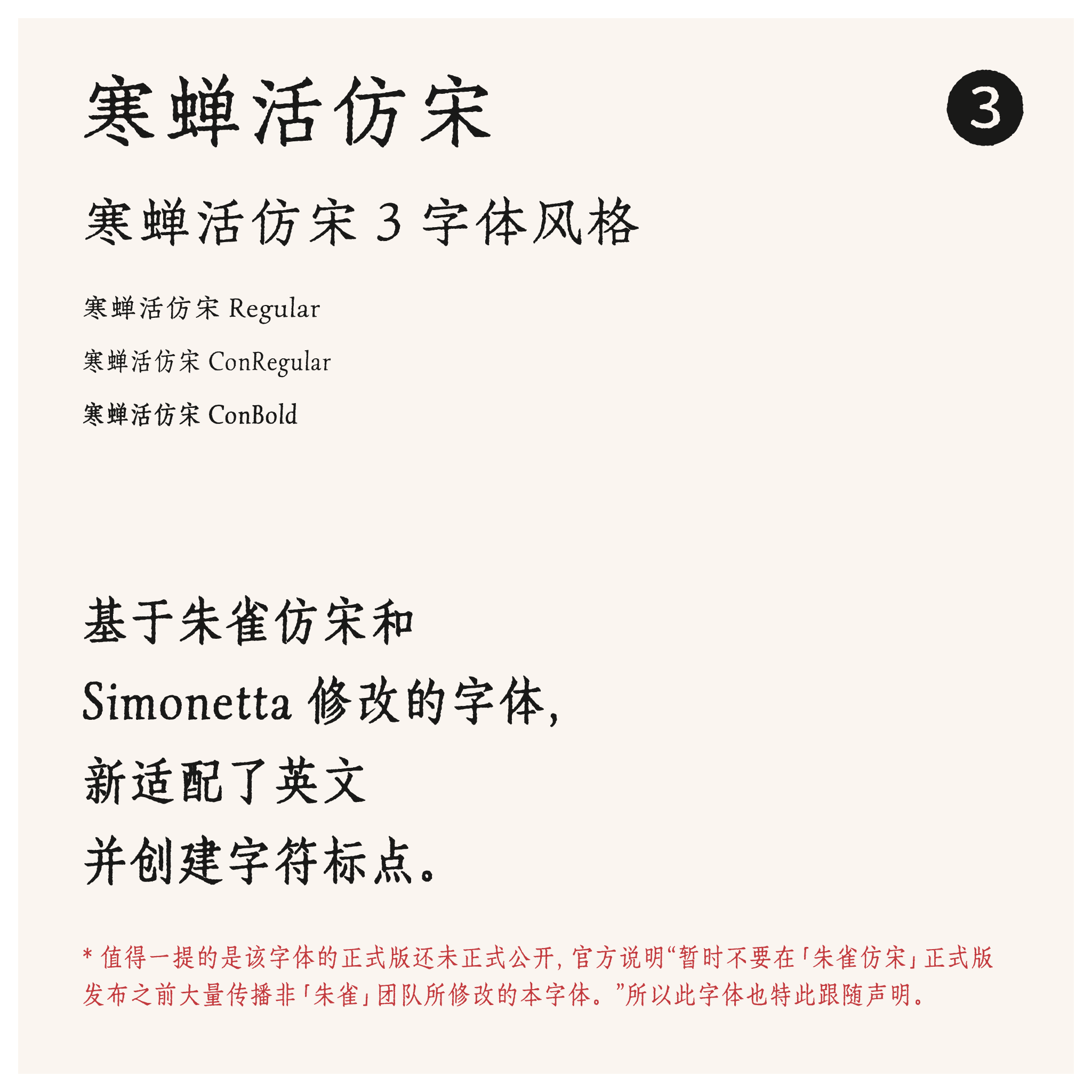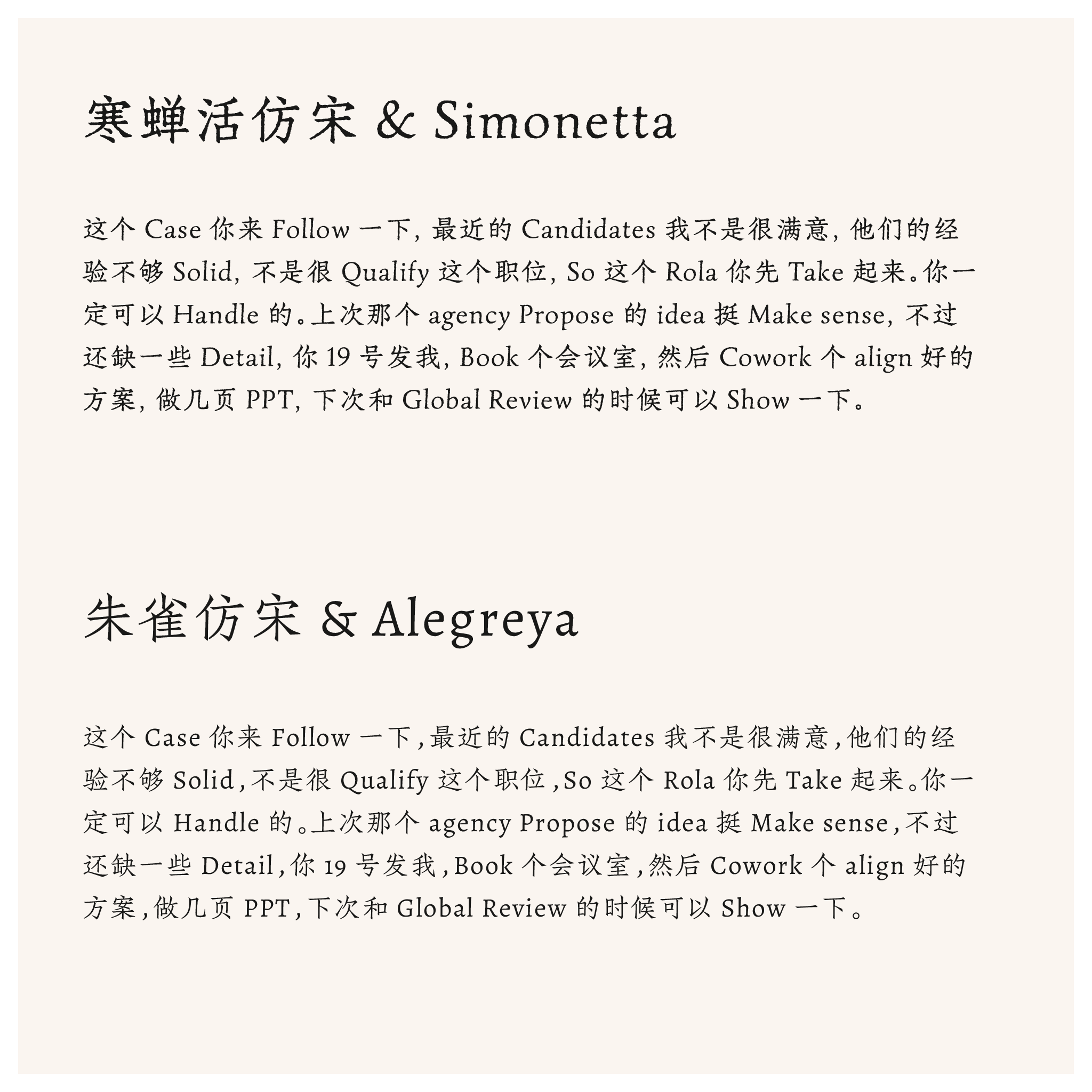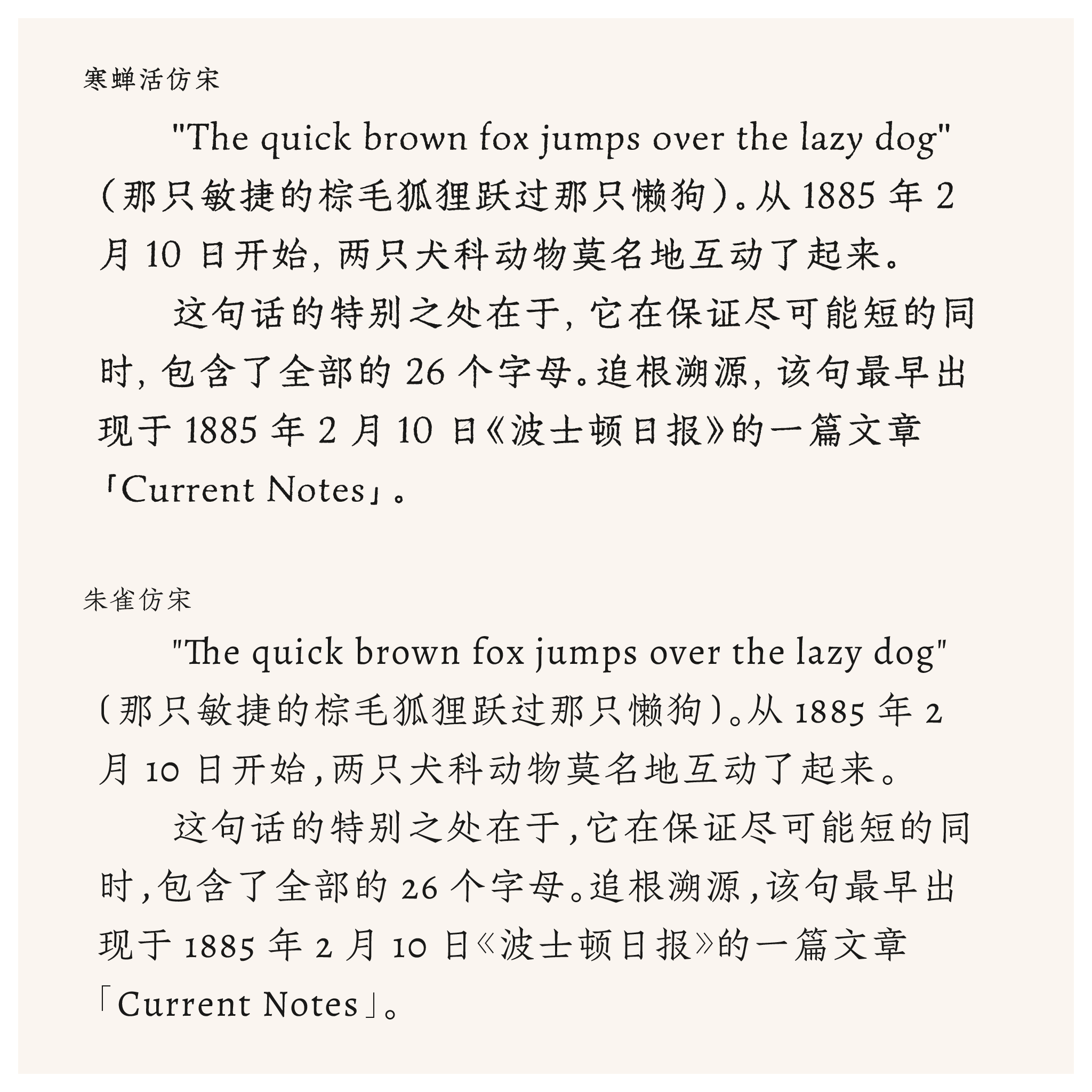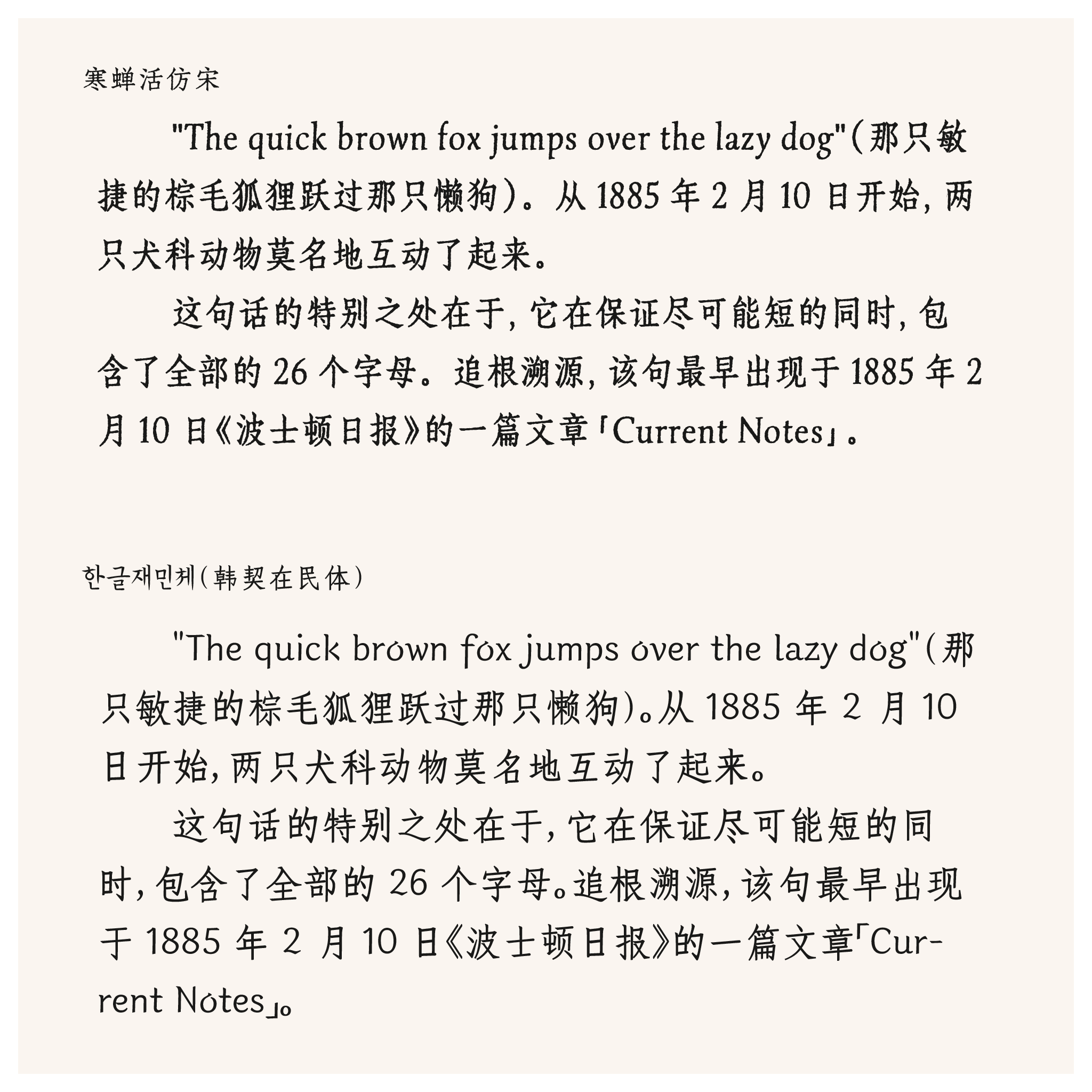
寒蝉活仿宋是一款融合经典与现代设计的字体,其基础源自朱雀仿宋与西文字体Simonetta的精心结合。设计师在保留朱雀仿宋典雅的中文结构和传统韵味的同时,借鉴了Simonetta在西文排版中的优雅与可读性特点,对整体字形进行了细腻的调整与平衡。为了提升字体的适用性与表现力,此次修改特别针对英文字符进行了全面适配,不仅优化了字母的比例、间距与细节处理,使中西文混排时视觉协调自然,还全新设计了一套完整的字符标点符号,确保各类标点在造型风格上与主字体保持统一,进一步增强了版面的整体美感与专业度。这一过程体现了对传统汉字美学与现代排版需求的深刻理解与融合。
寒蝉活字系列,展示模拟印刷时轻度油墨溢出的活字“宋”。
寒蝉活字系列字体项目文档
寒蝉活黑体、寒蝉活宋体、寒蝉活仿宋、寒蝉活楷体、寒蝉活仿楷。
展示同一诗句“野田春水碧于镜”的不同中文字体呈现,包括寒蝉活黑体/宋体、思源黑体(模拟斑驳纹理)、源云明朝(朦胧效果)、汇文明朝(真实印刷扫描)的样式对比。
寒蝉活仿宋字体介绍,展示其三种风格(Regular、ConBold),说明基于朱雀仿宋和Simonetta修改,新适配英文并创建字符标点,注官方正式版未公开,勿大量传播非朱雀团队修改版。
展示两款中英文搭配字体的排版效果:第一款为寒蝉活仿宋与Simonetta,第二款为朱雀仿宋与Alegreya,均用含中英混合商务内容的示例文本呈现。
寒蝉活仿宋和朱雀仿宋字体的样本,展示英文句子“The quick brown fox jumps over the lazy dog”及其中文翻译和起源说明。
以寒蝉活仿宋、韩契在民体两种字体展示英文全字母句“The quick brown fox jumps over the lazy dog”的介绍,包含其中文译文与句子起源说明。